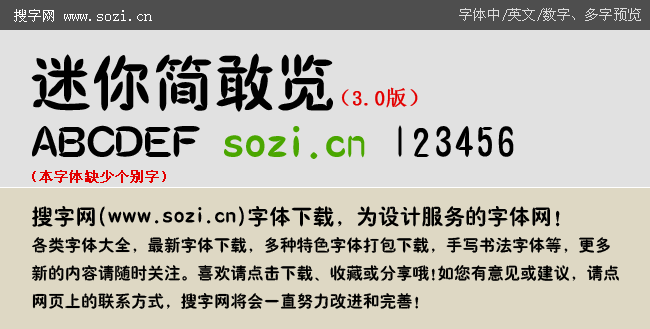
迷你簡(jiǎn)橄欖體
搜字網(wǎng)提供一款迷你簡(jiǎn)橄欖體POP藝術(shù)字體下載,迷你簡(jiǎn)橄欖體兩頭尖,中間呈凸圓弧形。筆畫簡(jiǎn)潔新穎,柔軟流暢,風(fēng)格稚氣質(zhì)樸,明快清純,藝術(shù)性較強(qiáng)。適合卡通畫冊(cè)、海報(bào)設(shè)計(jì)、包裝設(shè)計(jì)場(chǎng)合使用。